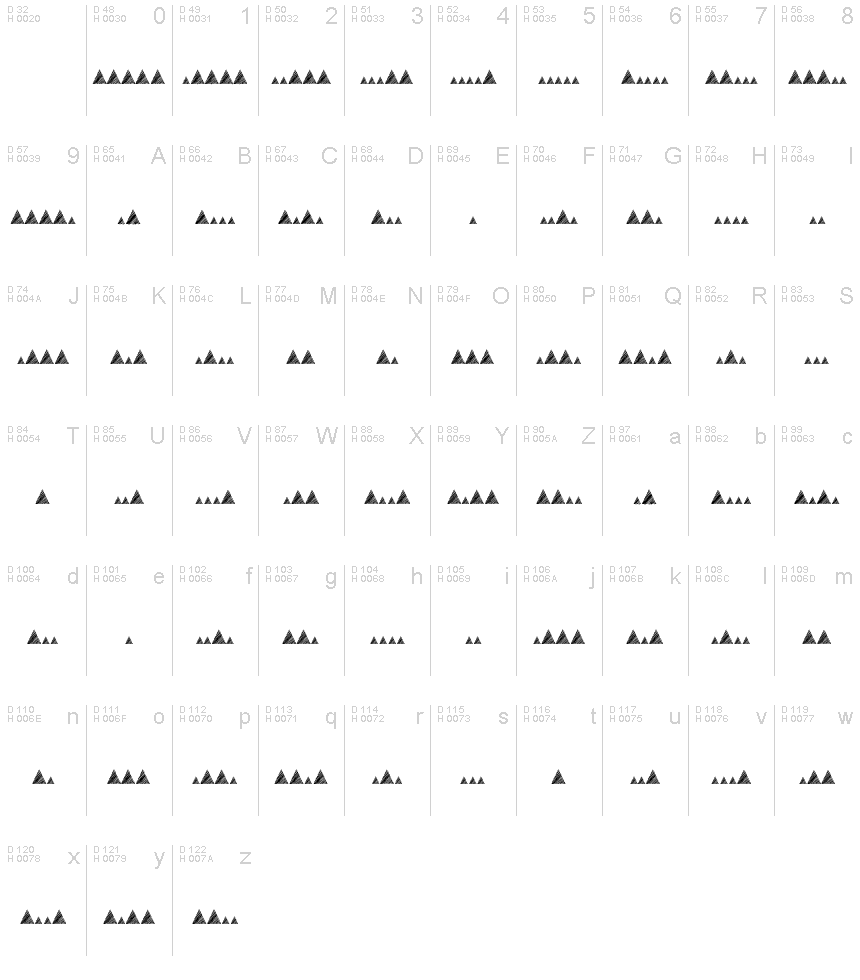
MorseMountainCode-Regular
Variacion del cdigo morse, en el que las lineas son remplazadas por tringulos grandes y los puntos por tringulos pequeos, semejando un hoja de Serrucho o una cordillera montaosa.
Morse Mountain Code